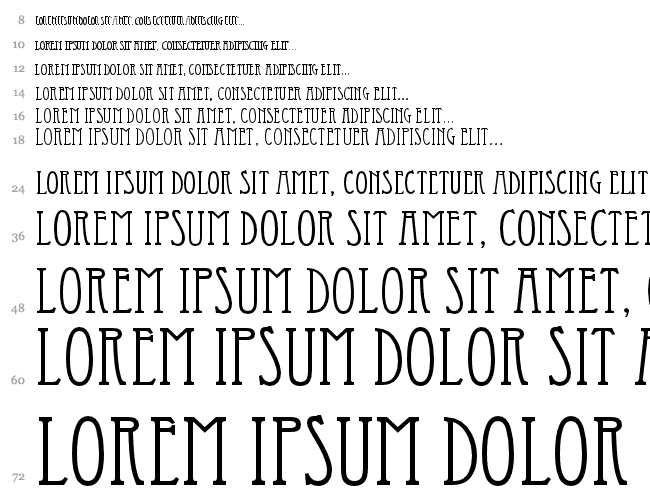
Jugendstil-Font, moderne Alternative gesucht.
ich bin auf der Suche nach einer Schriftart für eine Wortmarke.
Ich bin auf die Eccentric gestoßen. Gefällt mir schon sehr gut und passt auch zum Thema.
Es geht um ein Textillabel. Bereich Denim, Leder, Motorrad, Reiten. Moderne Klassiker, festes Material, lange Haltbarkeit.
Ist aber vll zu jugendstillastig. Vll habt ihr ja spontan modernere Alternativen im Kopf. Condensed als Schnitt ist super.
Würde mich auf jeden Fall freuen wenn ihr ein wenig Input für mich habt.
Da hast Du Recht. Bin auch erst Ideen am sammeln. :) Danke für Deinen Vorschlag, ist mir nur zu "verspielt".
… Ich bin auf die Eccentric gestoßen. …
war vor kurzem auf einem Vortrag auf dem die Delvard vorgestellt wurde, hat was jugendstilhaftes an sich, trotzdem sehr modern. Vielleicht gefällt sie dir ja.